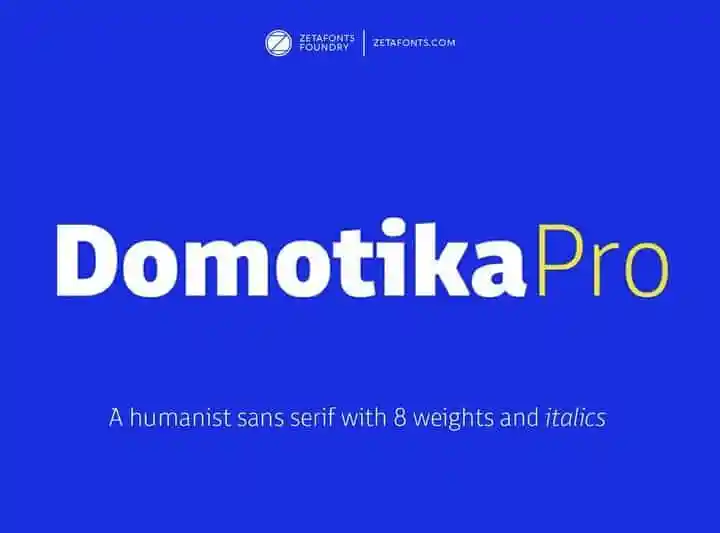
Domotika Pro Sans Serif Font
Bem-vindo à Domotika Pro Sans Serif Font! Inspirada por práticas arquiteturais, essa tipografia serifless é uma criação clássica e eterna que mantém um olhar pragmático mas não abandona a elegância. Ela une formas humanistas abertas com curvas levemente calligráficas nos fins de letras, equilibrando uma leitura precisa com um design expressivo. O nome da fonte se homenageia à ciência do conforto em casa e suas tecnologias robóticas domésticas, criando um design que atende às necessidades funcionais sem sacrificar a beleza. Ideal para ambientes contemporâneos e minimalistas, Domotika Pro é uma escolha perfeita para criar designs únicos com estilo. Seja em logomarcas, posters ou layouts web modernos, essa fonte oferece a precisão que você precisa, ao mesmo tempo que adiciona um toque de elegância única. Não hesite em baixar e experimentar Domotika Pro – é uma escolha inteligente para qualquer projeto de design atualizado.